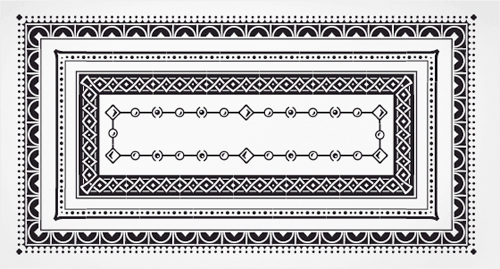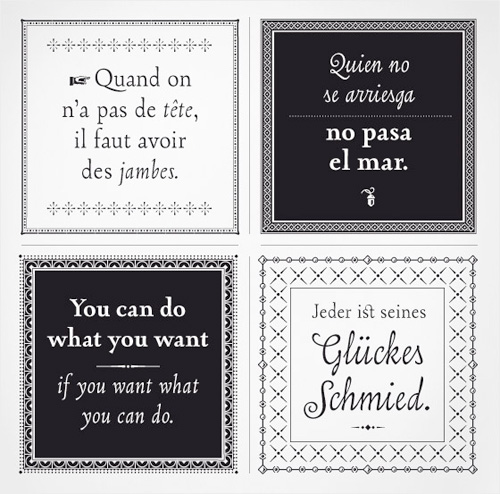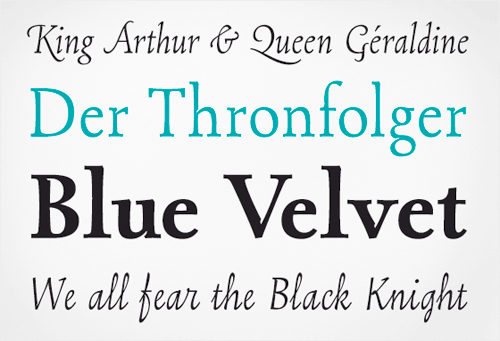
Von oben nach unten: Opal Italic (Swash), Opal Regular, Opal Bold und Opal Script. Die Schriftfamilie Opal enthält neben der Kursiv-Variante, einen Script-Schnitt, bei dem die Buchstaben wie bei einer Schreibschrift verbunden sind.
Von oben nach unten: Opal Script (Swash), Opal Regular (Small Caps), Opal Bold und Opal Italic. Neben den Kursiv- und Fett-Varianten hat Opal als Besonderheit eine passende Script-Version. Opal Script eignet sich hervorragend, um dem Text zusätzliches Gewicht zu verleihen, oder als Alternative zur Kursivschrift.
Darüber hinaus enthält jeder der Opal-Schnitte diverse Ornamente, Pfeile, Hände, etc.
Außerdem hat jeder Opal-Schnitt ein Set aus Rahmenelemente, die man je nach Bedarf der gewünschten Größe und Form anpassen kann.
Mit etwas Sorgfalt kann der Designer mit dieser Schriftfamilie exklusive, traditionelle Arbeiten erstellen.
Hannes von Döhren in seinem Berliner Atelier, bei der Arbeit an der Schriftfamilie Opal.
Opal is a text face with a noble feeling, yearning for luxury and still delivering. Because of the long ascenders that rise clearly above the capital letters, Opal should be set with generous line spacing. The typeface's design has the attributes of the oldstyle Renaissance serifs, yet Opal is not based on any specific predecessors. Through undulating strokes and sharp corners, a cutout feeling is created; Opal's letters sport inktraps at stroke junctions, which this strengthen this image in larger point sizes even further. In total, the letterforms have clear emphasis on their verticals and horizontals; they do not fear the weight on their curves. In addition to an Italic and Bold variant, Opal has a Script member of the family. Opal Script is perfectly suited for additional text emphasis, or as an alternative to the typeface's Italic.